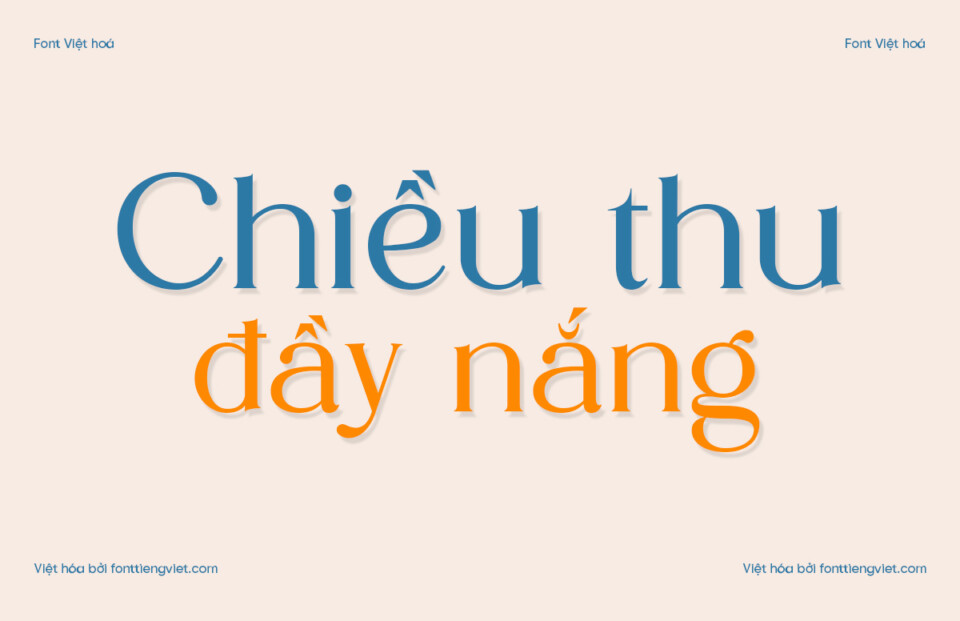
Font Việt hóa 1FTV VIP Honera
Trong thế giới thiết kế đồ họa hiện đại, việc lựa chọn một bộ font phù hợp đóng vai trò quyết định đến linh hồn của tác phẩm. Font Việt hóa 1FTV VIP Honera nổi lên như một lựa chọn hàng đầu cho những ai đang tìm kiếm sự kết hợp hoàn hảo giữa nét cổ điển và hơi thở đương đại. Đây là một bộ Font Miễn Phí được tinh chỉnh kỹ lưỡng, giúp các nhà sáng tạo nội dung tại Việt Nam dễ dàng thể hiện ý tưởng mà không lo lỗi font hay thiếu dấu tiếng Việt. Với cấu trúc thanh mảnh nhưng chắc chắn, bộ chữ này mang lại cảm giác chuyên nghiệp, tinh tế, cực kỳ phù hợp cho các dự án đòi hỏi tính thẩm mỹ cao và sự chỉn chu trong từng chi tiết nhỏ nhất.
Đặc điểm nổi bật của Font Việt hóa 1FTV VIP Honera
Thiết kế Serif tinh tế và đẳng cấp
Bộ Font Việt hóa 1FTV VIP Honera thuộc dòng font Serif (có chân) với các đường nét được gọt giũa vô cùng sắc sảo. Điểm đặc biệt của nó nằm ở sự tương phản nhẹ nhàng giữa các nét thanh và nét đậm, tạo nên một nhịp điệu thị giác dễ chịu cho người xem. Các ký tự tiếng Việt như ă, â, đ, ơ, ư được đội ngũ 1FTV chăm chút tỉ mỉ, đảm bảo các dấu thanh không bị dính vào chữ hay làm mất đi cấu trúc nguyên bản của font. Điều này giúp văn bản luôn giữ được sự cân đối, hài hòa dù bạn đang trình bày một đoạn văn dài hay chỉ là một dòng tiêu đề ngắn gọn trên bìa sách hoặc tạp chí thời trang.
Khả năng ứng dụng đa dạng trong thực tế
Không chỉ dừng lại ở các thiết kế in ấn, Font Việt hóa 1FTV VIP Honera còn thể hiện ưu điểm vượt trội khi được sử dụng trong các sản phẩm kỹ thuật số. Bạn có thể dễ dàng bắt gặp bộ font này trên các website cao cấp, các bài trình chiếu PowerPoint chuyên nghiệp trong môi trường học đường hoặc các thiết kế thiệp mời sang trọng. Đối với các bạn học sinh và sinh viên, đây là công cụ đắc lực để làm nổi bật các bài tiểu luận hoặc dự án cá nhân. Sự thanh lịch của Honera giúp nâng tầm giá trị nội dung, khiến người xem cảm nhận được sự đầu tư và tâm huyết của người thực hiện bài thiết kế đó một cách tự nhiên nhất.
Cách tối ưu hóa Font Việt hóa 1FTV VIP Honera trong thiết kế
Lưu ý về kích thước và khoảng cách chữ
Để Font Việt hóa 1FTV VIP Honera phát huy tối đa vẻ đẹp, người dùng nên chú ý đến khoảng cách giữa các chữ cái (kerning). Do đặc thù có chân mảnh, việc để khoảng cách quá hẹp có thể gây rối mắt, trong khi khoảng cách quá rộng lại làm mất đi tính liên kết của từ. Khi sử dụng làm tiêu đề chính, hãy thử tăng nhẹ khoảng cách dòng để tạo không gian thở cho thiết kế. Ngoài ra, việc kết hợp Honera với một font Sans-serif đơn giản cho phần nội dung sẽ tạo nên một cặp bài trùng hoàn hảo, giúp phân cấp thông tin rõ ràng và thu hút sự chú ý của độc giả vào những vị trí quan trọng nhất trên trang giấy hoặc màn hình.
Lý do nên lựa chọn font từ cộng đồng 1FTV